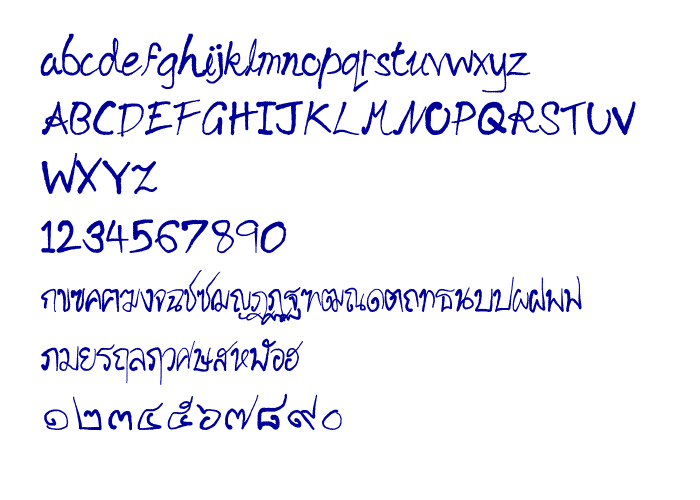
ฟอนต์แรกในชีวิตนะคะ  ช่วยแนะนำติชมให้ด้วยค่ะ
ลืมบอกน่ะค่ะ ตัวอักษรนี้ชื่อ -Yuri_handwriting_2006
ปล่อยวันที่ 19 กรกฎาคม 2549 นี้ค่ะ
เละได้ใจ ฮิ้ววว
555 คุณยูริ ร่างแบบ หรือยังครับ
เปลี่ยนปากกาบ่อยจังนะครับ เอือม
ลายมือเหมือนใช้ปากกาหัวคอแร้ง (เค้าเรียกกันแบบนี้รึเปล่าอ่ะ) เขียนเลย
ดูไกล ๆ นึกว่าใช้ปากกาเขียนบนกระดาษจิง ๆ แฮะ